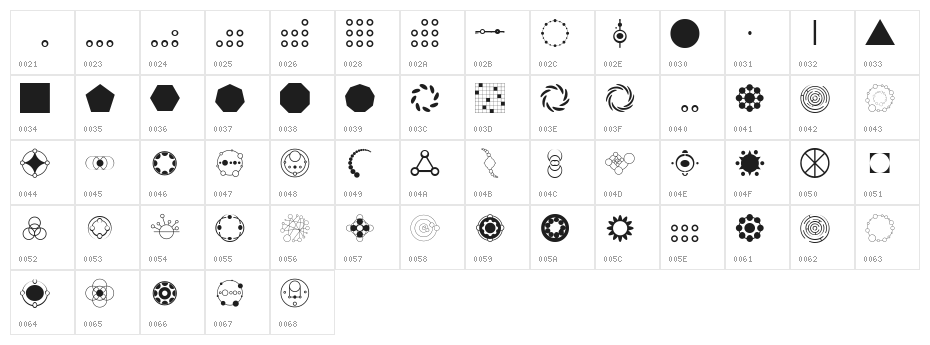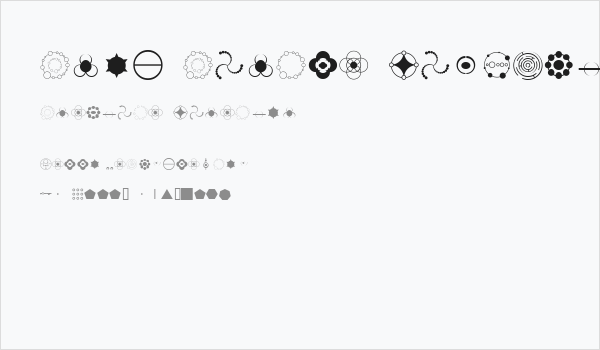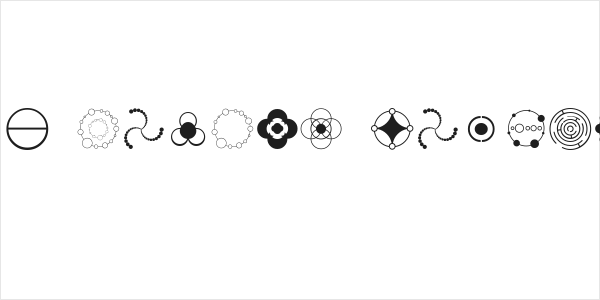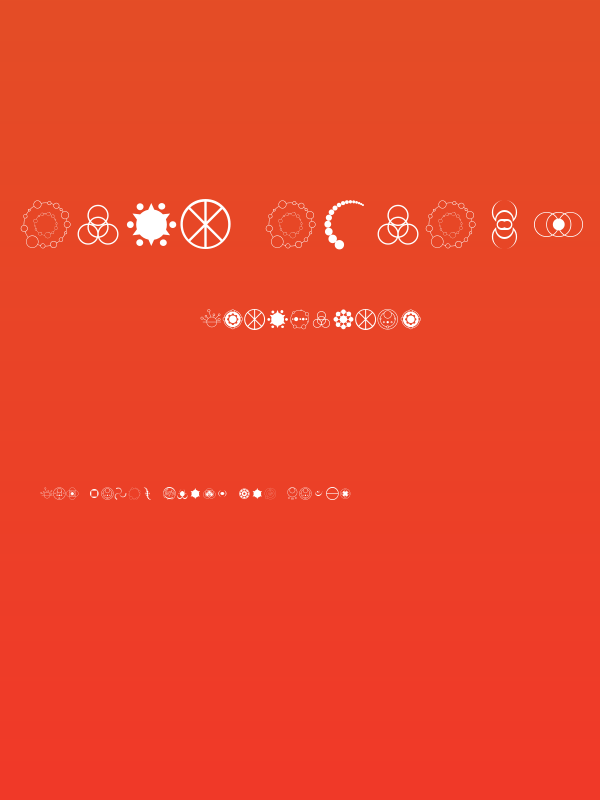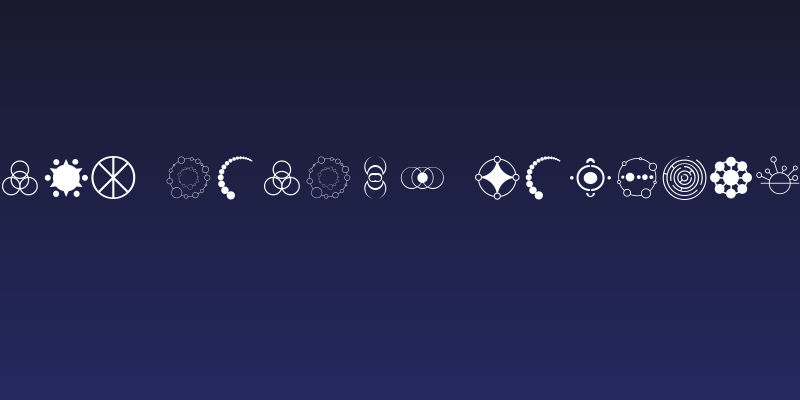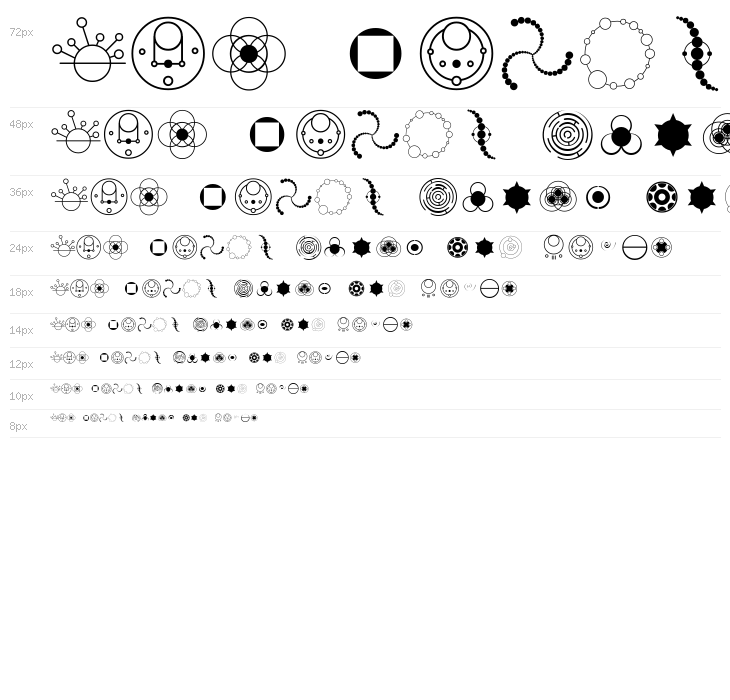
Crop Circle Dingbats Font
| 名前 | Crop Circle Dingbats |
| カテゴリ | Images & Symbols |
| 全体的なスタイル | Decorative, Futuristic, Abstract |
| 用途 | Icons, Borders, Decorative elements, Themed graphics |
| おすすめプロジェクト | Posters, album covers, sci-fi themed graphics, decorative dividers, branding for alternative or mystical products. |